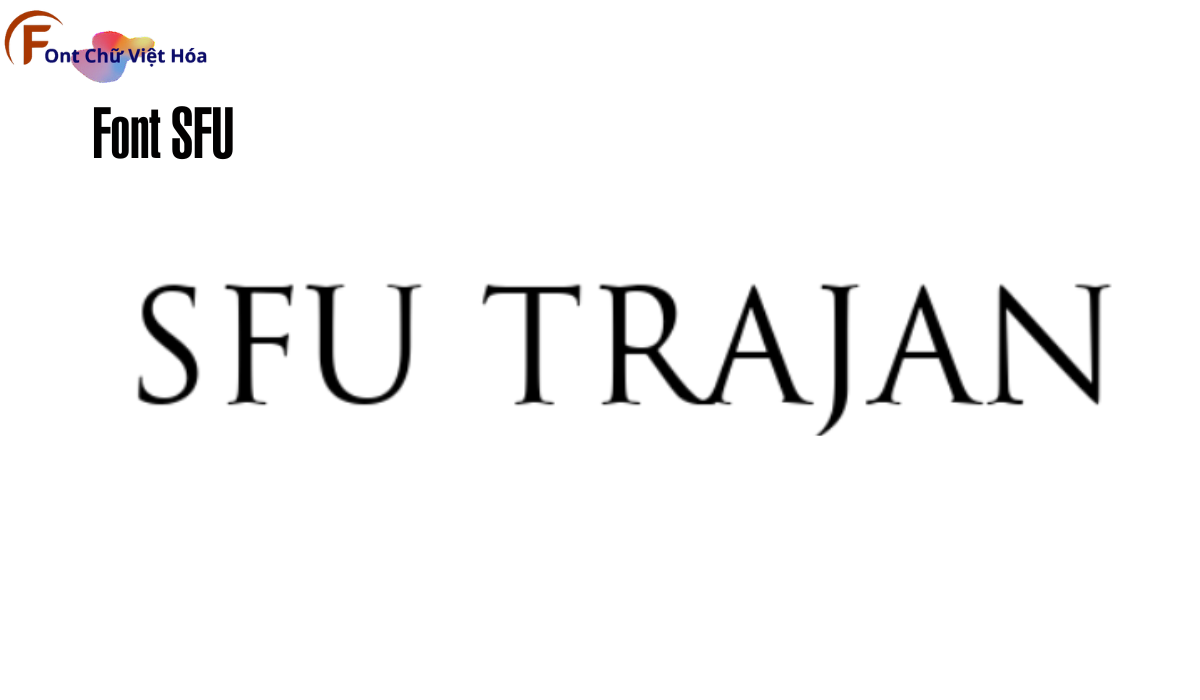
Font SFU Trajan Việt Hóa
Tác giả: Adobe
Ngôn ngữ: Tiếng Việt, Tiếng Anh
Bộ Font: SFU
Phân loại: Cổ điển, Trang trọng
Kiểu chữ: Chữ có chân
Font SFU Trajan Việt Hóa là một font chữ độc đáo, mang phong cách serif cổ điển với các đường nét thanh thoát và tinh tế, thuộc bộ font SFU. Thiết kế của SFU Trajan tập trung vào sự sang trọng và dễ đọc, đặc biệt phù hợp cho các thiết kế đòi hỏi tính thẩm mỹ cao như sách, báo, và tài liệu. Với tỷ lệ chữ cân đối và các đường nét rõ ràng, font này tạo ra ấn tượng thị giác mạnh mẽ và giúp tối ưu hóa không gian trong thiết kế. Font này cũng đã được Việt hóa, mang đến sự linh hoạt và tiện dụng cho các dự án thiết kế bằng tiếng Việt.